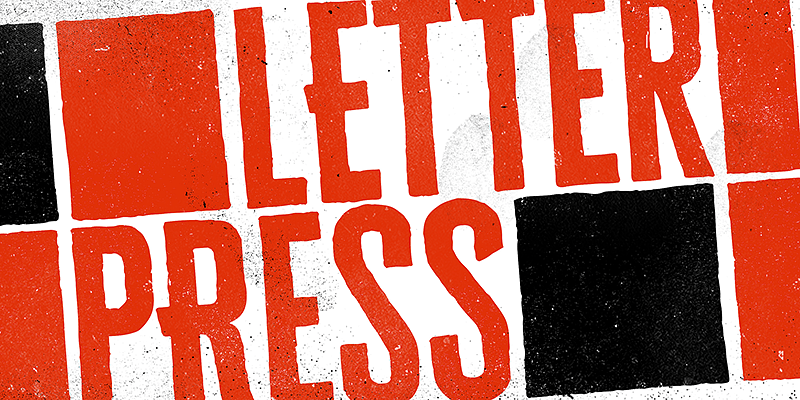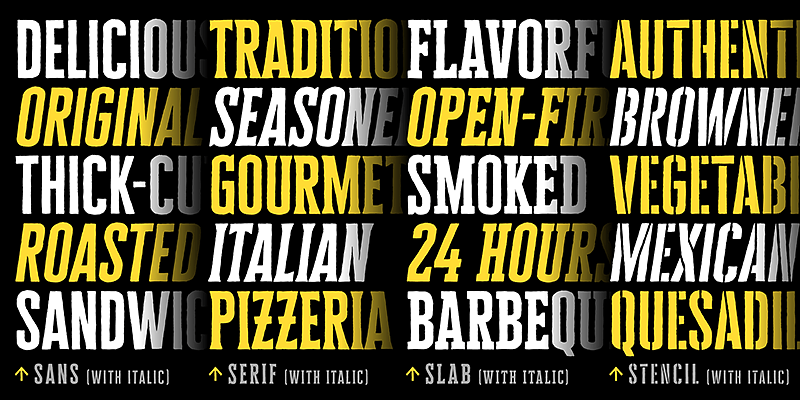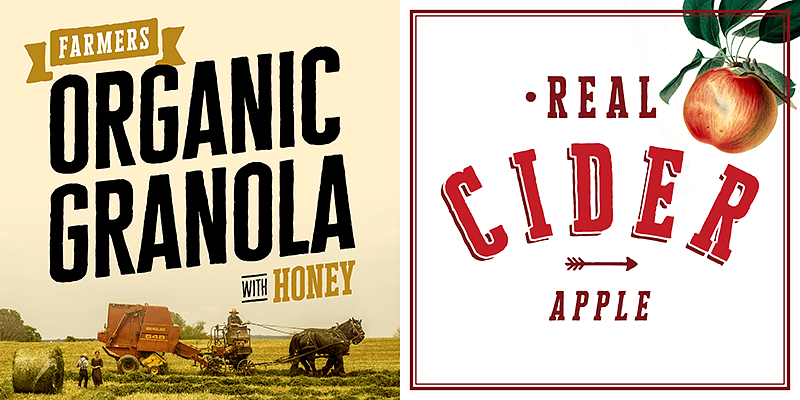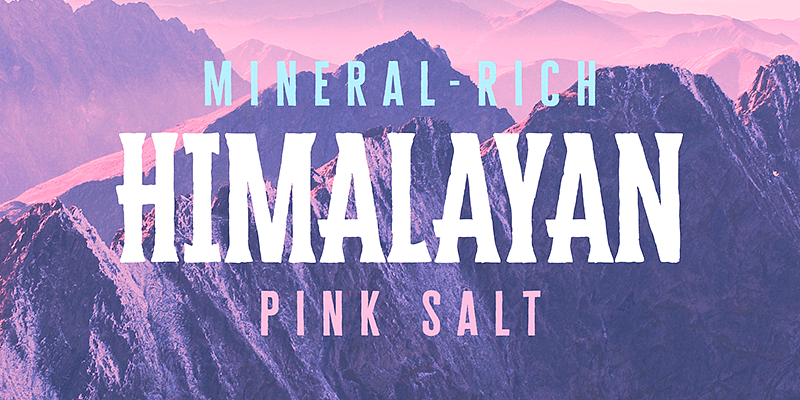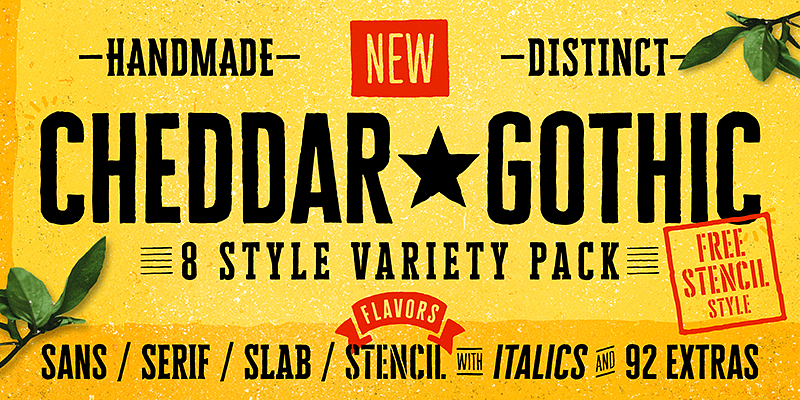
Con un’enfasi sui font progettati per essere utili e unici, Adam Ladd crea font con un fascino diversificato che spazia dall’estetica moderna e vintage negli stili sans serif, serif e script. La sua esperienza come direttore artistico presso due delle pubblicazioni di design più apprezzate, le riviste HOW e PRINT, segnala il suo lavoro di type designer. Individui e aziende di grandi dimensioni in molti settori hanno concesso in licenza i suoi font, tra cui Disney, Whole Foods, Blizzard Entertainment e Penguin Random House.